Trong các dự án kiến trúc mang phong cách truyền thống hoặc những không gian nghỉ dưỡng hướng đến vẻ đẹp hoài cổ, việc lựa chọn phông chữ đóng vai trò quan trọng để truyền tải linh hồn của tác phẩm. Font chữ Hán Việt hóa là bộ sưu tập các kiểu chữ mô phỏng cấu trúc của chữ Hán và chữ Nôm nhưng được tinh chỉnh để gõ được bảng chữ cái tiếng Việt.
Đặc điểm thẩm mỹ độc đáo của bộ font chữ Hán Việt hóa
Sức hút của dòng phông chữ này nằm ở cách mô phỏng các kỹ thuật viết bút lông kinh điển như lối chữ Khải, chữ Lệ hay chữ hành. Các nét chữ thường có cấu trúc vuông vức, vững chãi, tạo cảm giác trang trọng và cổ kính cho văn bản. Phiên bản font chữ Nôm Việt hóa đã được xử lý khéo léo để các dấu thanh tiếng Việt (huyền, sắc, hỏi, ngã, nặng) nằm gọn trong khung hình vuông của ký tự, giúp tổng thể trình bày không bị rời rạc hay lỗi nhịp so với cấu trúc nguyên bản.
Sự ổn định về mặt thị giác của dòng font này còn giúp người xem cảm nhận được sự giao thoa giữa quá khứ và hiện tại. Thay vì sử dụng những phông chữ Latinh hiện đại có phần mảnh mai, các nét chữ dày và dứt khoát của phong cách Hán Nôm tạo nên điểm nhấn mạnh mẽ trên các bề mặt vật liệu tự nhiên như gỗ, đá hoặc gạch gốm. Đây là phương án hiệu quả để nâng tầm giá trị cho các công trình có xu hướng bảo tồn văn hóa hoặc kiến trúc Zen tự tại.
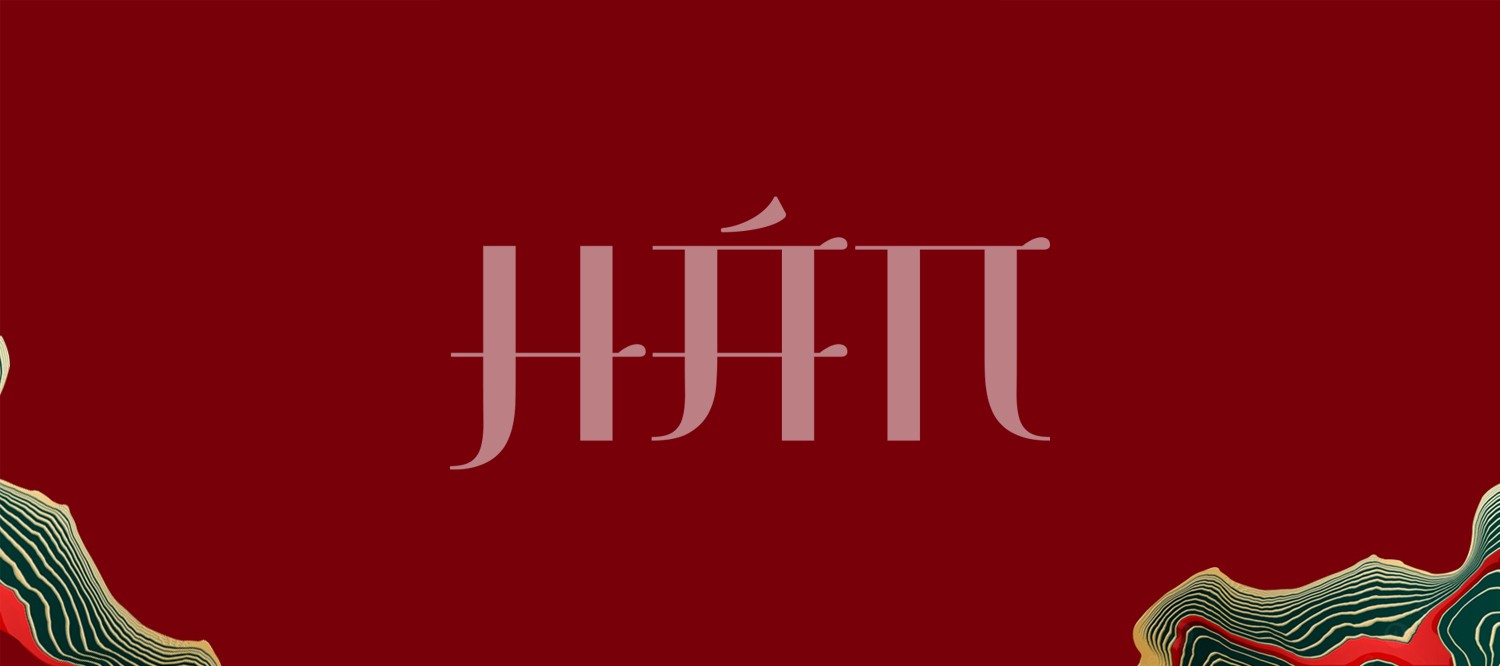
Lời khuyên thiết kế: Khi sử dụng font chữ Hán Việt hóa, bạn nên ưu tiên các tông màu trầm như đen mực tàu, đỏ son hoặc vàng đồng trên nền vật liệu tối màu. Việc phối hợp cùng một phông chữ không chân tối giản cho phần thông tin phụ sẽ giúp bản thiết kế đạt được sự cân bằng, tránh cảm giác nặng nề cho người xem.
03 Ứng dụng đưa font chữ Hán Việt hóa vào thực tế kiến trúc
Nhờ diện mạo giàu tính biểu tượng và sự trang nghiêm, bộ phông chữ này mang lại giá trị cao trong khâu trang trí các công trình xây dựng có yếu tố truyền thống:
- Bảng nhận diện cho Homestay & Khu nghỉ dưỡng Zen: Những nét chữ giả cổ rất ăn ý khi xuất hiện trên biển hiệu bằng gỗ thịt hoặc đá tự nhiên tại các khu nhà lắp ghép nghỉ dưỡng. Điều này giúp du khách cảm nhận được không gian tĩnh tại ngay từ khi bước chân vào công trình.
- Trang trí không gian nội thất văn hóa: Bạn có thể dùng font này để thiết kế các bức hoành phi, câu đối hoặc decal dán tường tại phòng khách, khu vực trà đạo nhằm tạo điểm nhấn đầy thẩm mỹ và chiều sâu cho không gian sinh hoạt.
- Hồ sơ thuyết minh dự án bảo tồn: Sử dụng font chữ nôm Việt hóa cho các tiêu đề chương hoặc sơ đồ vị trí giúp hồ sơ trở nên chuyên nghiệp, thể hiện sự am hiểu và tôn trọng của đơn vị thiết kế đối với bối cảnh lịch sử của dự án.
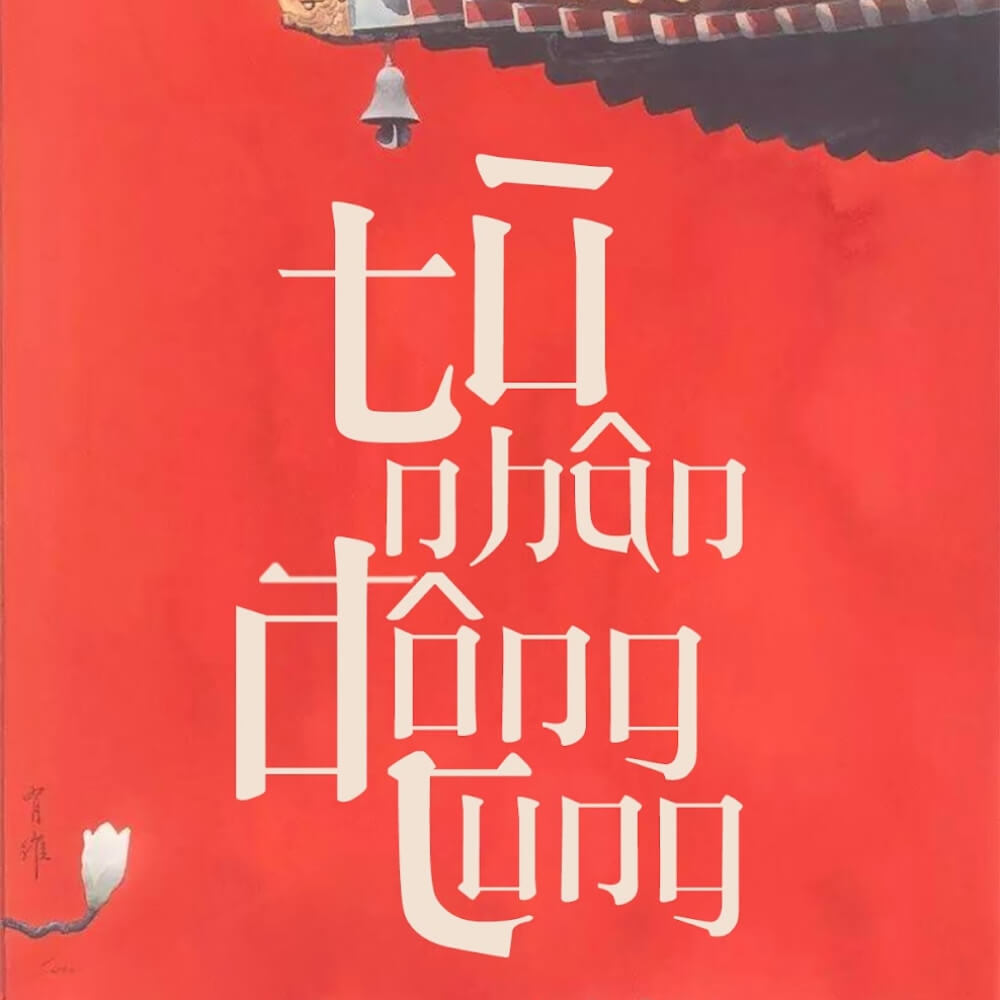
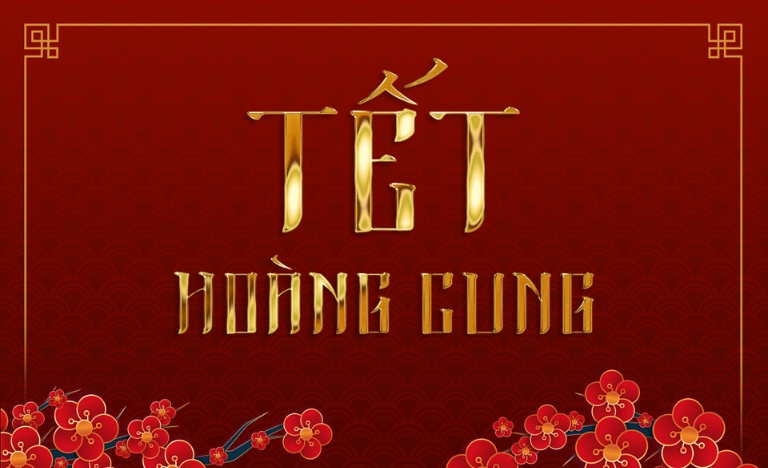
03 Lưu ý để trình bày phông chữ Hán Nôm hài hòa và sang trọng
Để khai thác hiệu quả vẻ đẹp của dòng font đặc thù này mà không làm rối mắt người đọc, người thiết kế nên lưu tâm một số kinh nghiệm sau:
- Kiểm soát mật độ chữ: Do cấu trúc chữ Hán Nôm thường dày và chiếm không gian, bạn nên nới rộng khoảng cách giữa các chữ cái (tracking) và khoảng cách dòng. Việc để các ký tự quá sát nhau sẽ khiến văn bản bị bết dính và khó nhận diện mặt chữ.
- Hạn chế dùng cho đoạn văn dài: Chỉ nên sử dụng phông chữ này cho tiêu đề, slogan hoặc các câu trích dẫn ngắn. Việc lạm dụng cho toàn bộ nội dung thuyết minh kỹ thuật sẽ gây mỏi mắt và làm giảm tính chuyên nghiệp của bản vẽ.
- Lựa chọn kích thước hiển thị: Font phong cách Hán Việt phát huy hiệu quả thị giác tốt ở kích thước trung bình đến lớn. Ở kích thước quá nhỏ, các chi tiết nét cọ mô phỏng có thể bị nhòe, gây khó khăn cho việc quan sát từ xa.